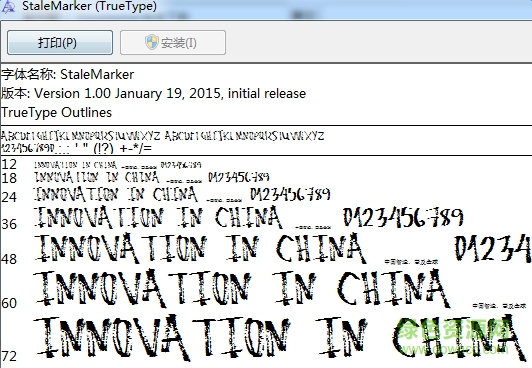
StaleMarker字體是一款極具個(gè)性的英文字體,文字排版、海報(bào)廣告設(shè)計(jì)、藝術(shù)設(shè)計(jì)等方面都可以使用,小編為大家?guī)砻赓M(fèi)下載地址,大家快來綠色資源網(wǎng)踴躍下載哦!
StaleMarker字體,一款非常好看的個(gè)性英文字體,字形工整大氣,書寫流暢,可用于排版方面。喜歡的朋友就趕快來綠色資源網(wǎng)下載使用吧!